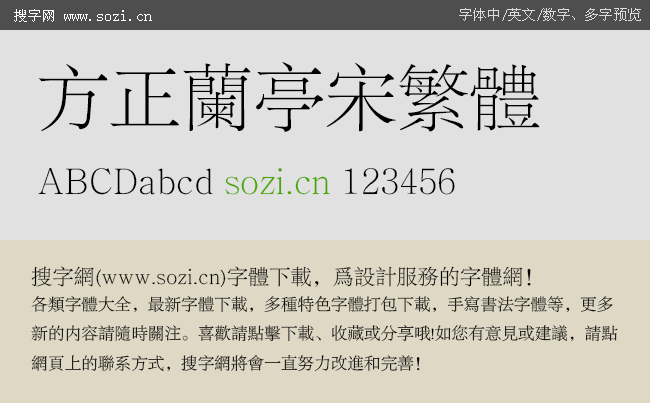
方正蘭亭宋繁體(FZLTSFW)
搜字網(wǎng)提供一款方正蘭亭宋繁體中文字體下載,方正粗雅宋是一款字形清秀的中文字體,該字體結(jié)構(gòu)優(yōu)美,識別性好,常用于產(chǎn)品設(shè)計、包裝印刷、報刊雜志、正文標(biāo)題、繪畫創(chuàng)作等廣告設(shè)計場合使用。